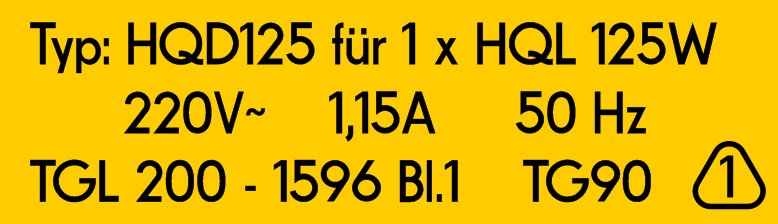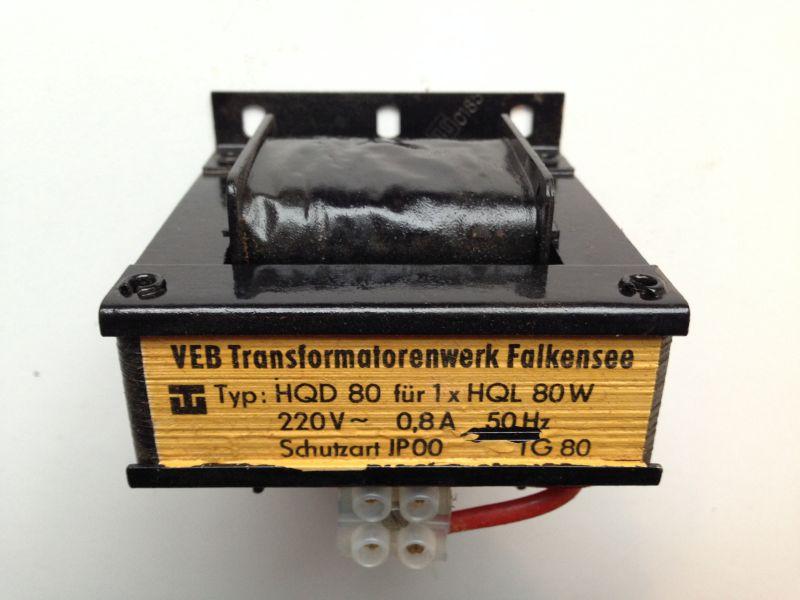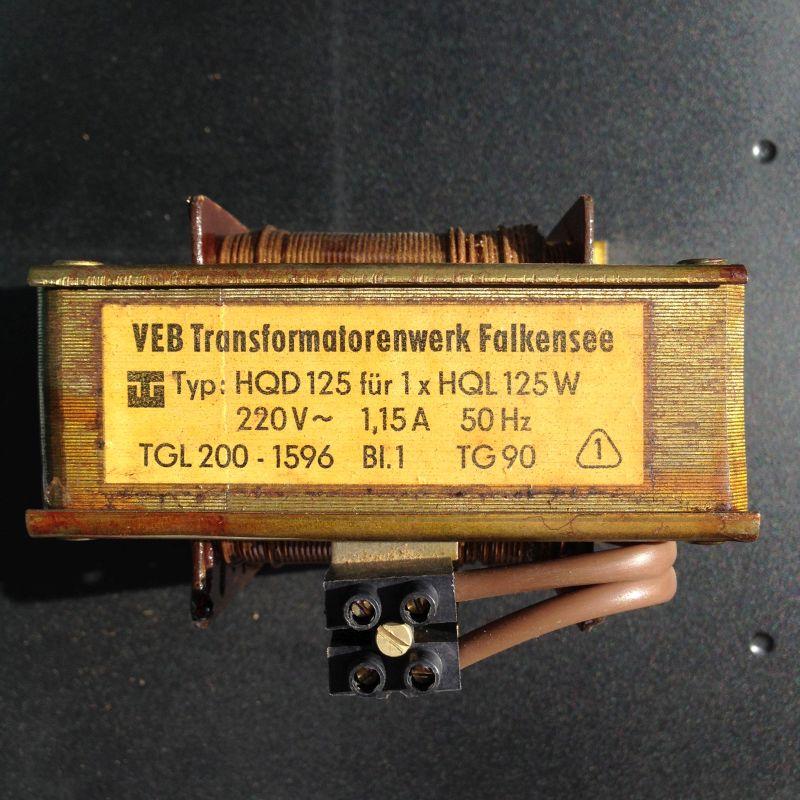
Schriftgesuch zu Typenschildern aus der DDR
ich hoffe hier eine Antwort wenigstens zur verwendeten Schrifttype an zwei Typenschildern von Elektroerzeugnissen aus der DDR zu erhalten.
Es geht konkret um diese beiden Schildchen mit ihren Schriften.
Gelöst von RobertMichael
Das abgerundete Dreieck hast du aber von Hand drum gemalt – oder, @catfonts? ;-)
Bitte nicht verwenden, die Fonts sind eine Zumutung.
Arno Drescher würde sich im Grab umdrehen wenn er diese Digitalisierung sieht.
Das abgerundete Dreieck hast du aber von Hand drum gemalt
Ja
Aber für solche Anwendungen, wie Ersatz-Typenschilder reicht das allemal. So voll glücklich bin ich auch nicht, hatte leider nur einen Typofix-Bogen zur Vorlage